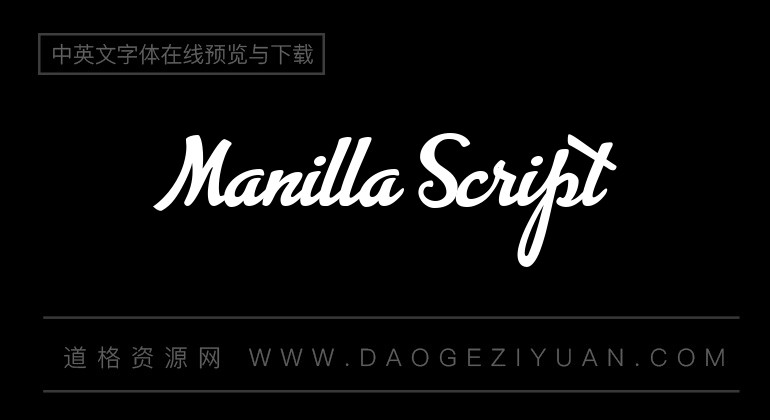
Manilla Script
Manilla Script 是一款古典经典的欧洲手写体字体,它具有流畅的线条和优美的形状,带有一种古老的复古风格,非常适合用于浪漫的文字排版、卡通形象或婚礼邀请函等场景。它的特点是字体细节丰富,笔画细腻,曲线优美,能够更好地展现出文字的魅力和精美。
Manilla Script是一款非常不错的手写艺术字体,具有很好的视觉感,适合于文化类的宣传设计、商业类品牌的广告和产品包装设计以及个性化文字排版等较多场景。
Manilla Script字符映射图